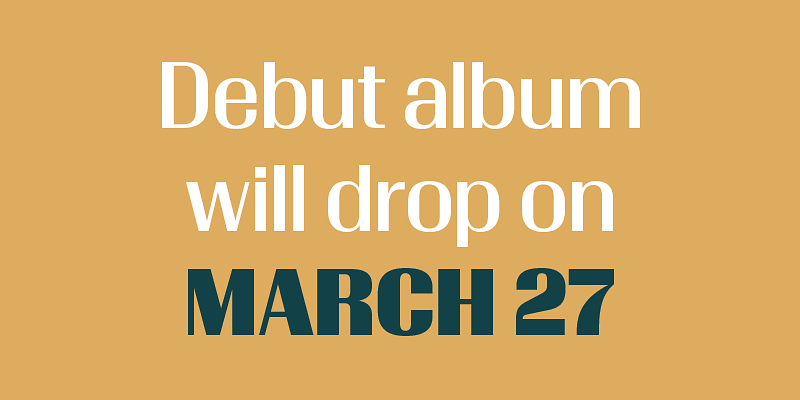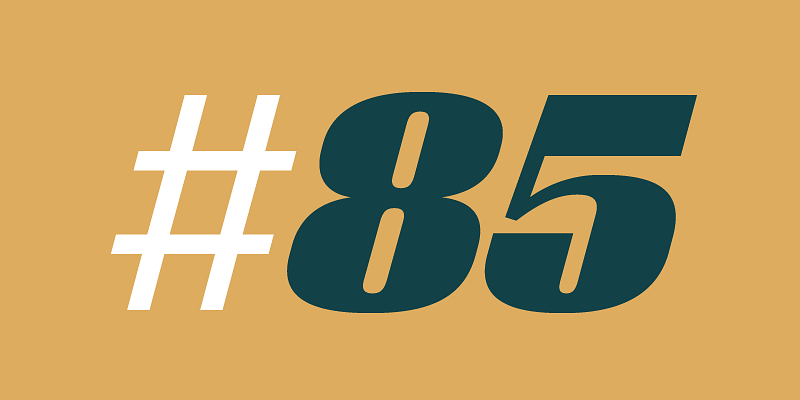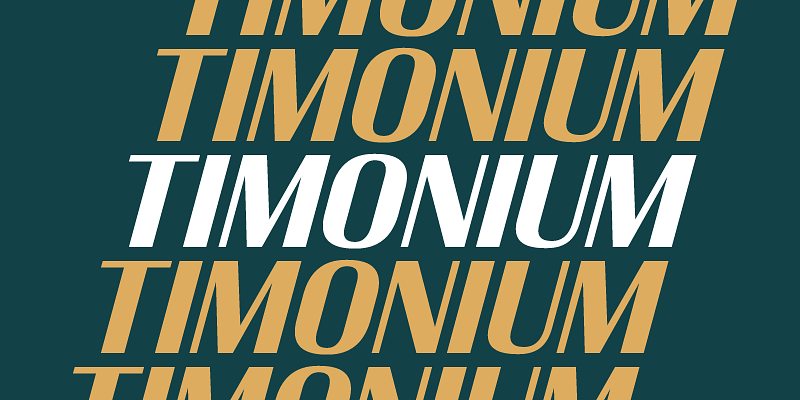
Timonium est une police Sans Serif originale aux accents optimistes. Ses formes épurées et contrastées sont idéales pour composer des messages tournés vers l’avenir, quel que soit le contexte.